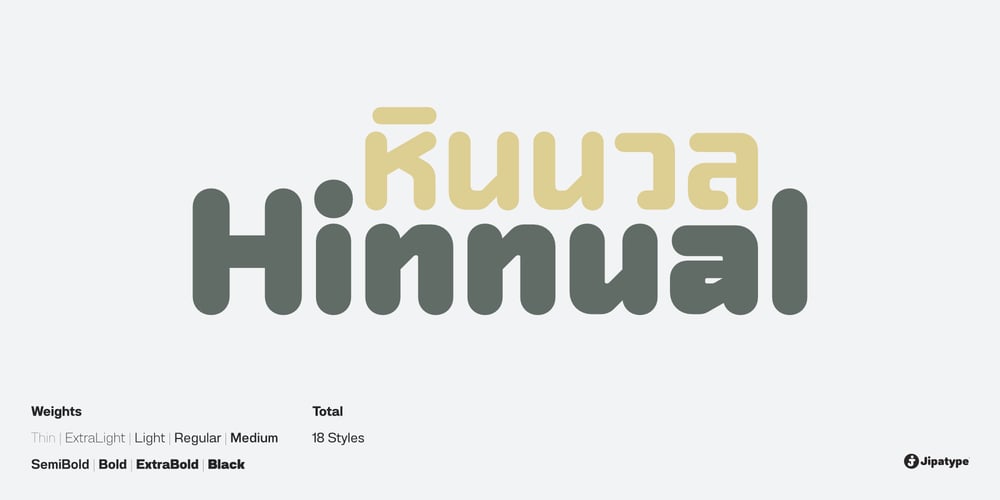
Hinnual Font Family was designed by Anupap Jaichumnan and published by Jipatype. Hinnual contains 18 styles and family package options. Hinnual เป็นฟอนต์ที่ผสมผสานระหว่างรูปทรงสี่เหลี่ยมและทรงกลมเพื่อสร้างสไตล์ที่ไม่เหมือนใคร ชื่อมาจากคำไทย 2 คำ คือ Hin แปลว่า หิน และ Nual แปลว่า อ่อน ผสมผสานองค์ประกอบที่แข็งและอ่อนนี้สะท้อนให้เห็นในแบบอักษร ซึ่งมีเส้นที่สะอาดตาและเส้นคมซึ่งถูกทำให้อ่อนลงด้วยมุมโค้งมน ฟอนต์มีให้เลือกถึง 18 แบบ มีตัวเลือกหลากหลายให้คุณได้เลือกใช้ Hinnual เหมาะอย่างยิ่งสำหรับใช้ในพาดหัวและพาดหัวย่อย ซึ่งลักษณะที่โดดเด่นสามารถช่วยดึงดูดความสนใจของผู้อ่านได้ เส้นสายที่สะอาดตาและสไตล์ที่เป็นเอกลักษณ์ยังทำให้เป็นตัวเลือกที่ยอดเยี่ยมสำหรับแบรนด์ โลโก้ และงานออกแบบอื่นๆ ที่ต้องการภาพลักษณ์ที่น่าจดจำ โดยรวมแล้ว Hinnual เป็นฟอนต์อเนกประสงค์และสะดุดตาที่ผสมผสานองค์ประกอบทั้งความแข็งแกร่งและความนุ่มนวล การออกแบบที่เป็นเอกลักษณ์ทำให้เป็นตัวเลือกที่ยอดเยี่ยมสำหรับนักออกแบบที่ต้องการสร้างผลงานที่น่าจดจำHinnual is a font that combines the square and rounded shapes to create a unique visual style. Its name comes from two Thai words – Hin, which means stone, and Nual, which means soft. This juxtaposition of hard and soft elements is reflected in the font’s design, which features clean, sharp lines softened by rounded corners. The font comes in 18 styles, providing a range of options for designers to choose from. Hinnual is particularly well-suited for use in headlines and sub-headlines, where its bold and distinctive appearance can help to grab the reader’s attention. Its clean lines and unique style also make it a great choice for branding projects, logos, and other design elements that require a memorable. Overall, Hinnual is a versatile and eye-catching font that combines elements of both strength and softness. Its unique design make it an excellent choice for designers looking to create impactful visual content.